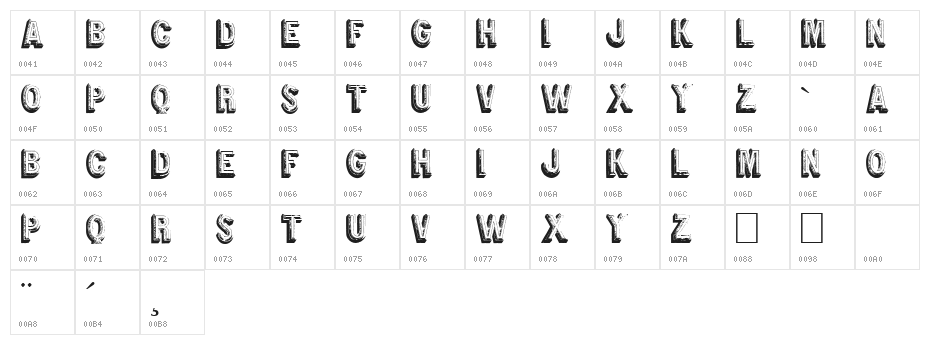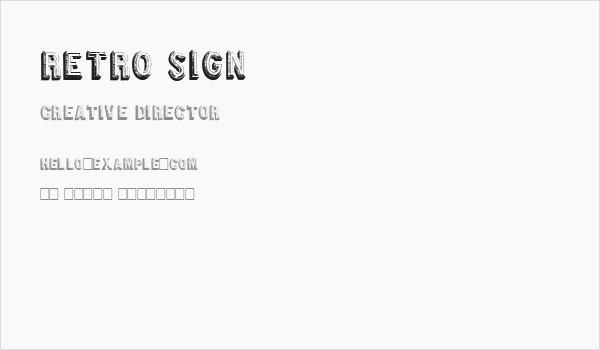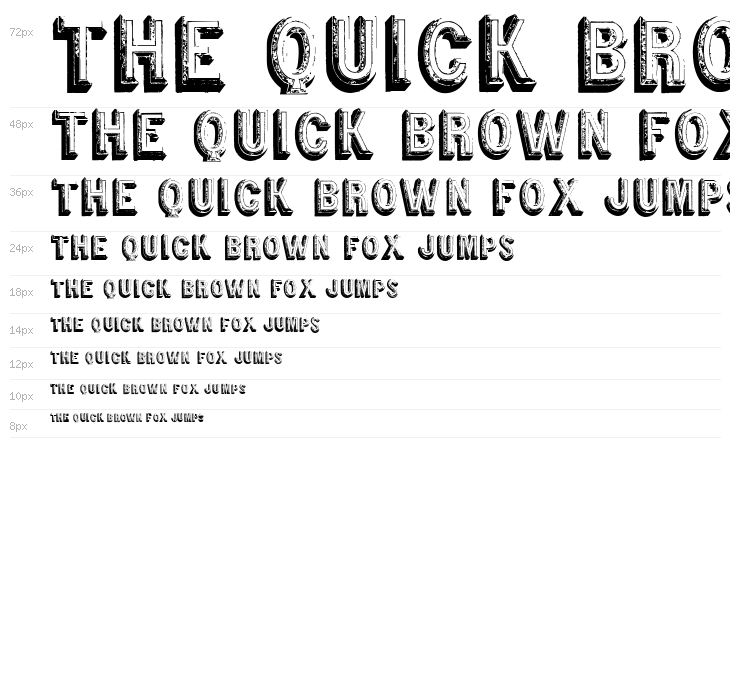
Retro sign Font
| Kategorien | 3D |
| Gesamtstil | Vintage |
| Vorgeschlagene Projekte | Ideal for vintage posters, retro-themed branding, signage, and album covers. |